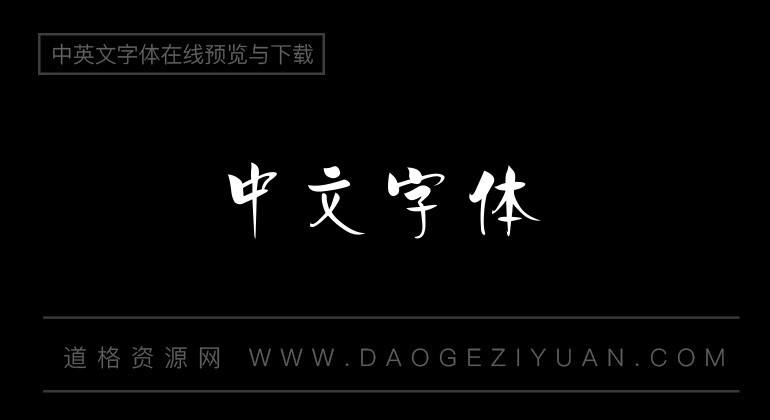
中国龙海报体
? 中国龙海报体是一款源自中国传统文化的中文字体,它采用汉字的自然笔画和笔锋,在字体的设计上更加符合中国传统文化的美感,使字体更加美观大方,更易于接受。字体的笔画细腻,线条优美,笔划端庄,笔画流畅,字体的结构具有统一性,字体的视觉效果也更加美观大方。
中国龙海报体是一款非常不错的手写艺术字体,具有很好的视觉感,适合于文化类的宣传设计、商业类品牌的广告和产品包装设计以及个性化文字排版等较多场景。